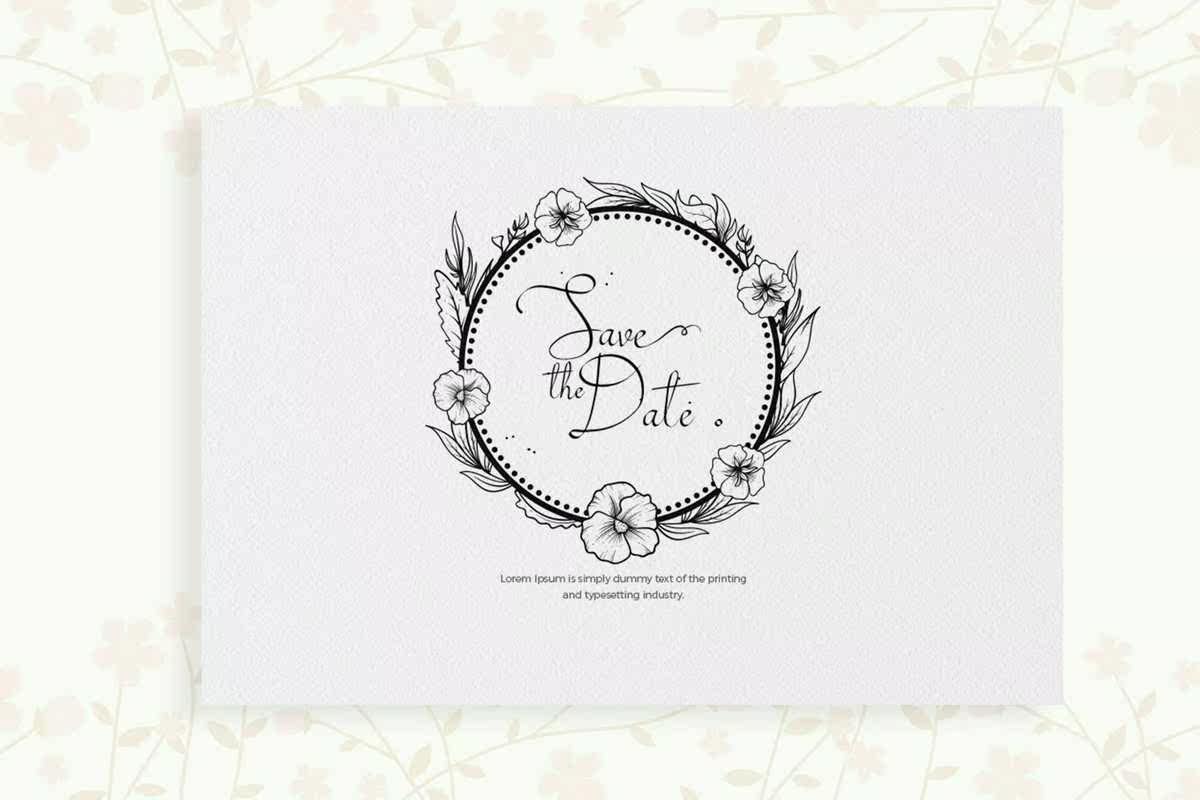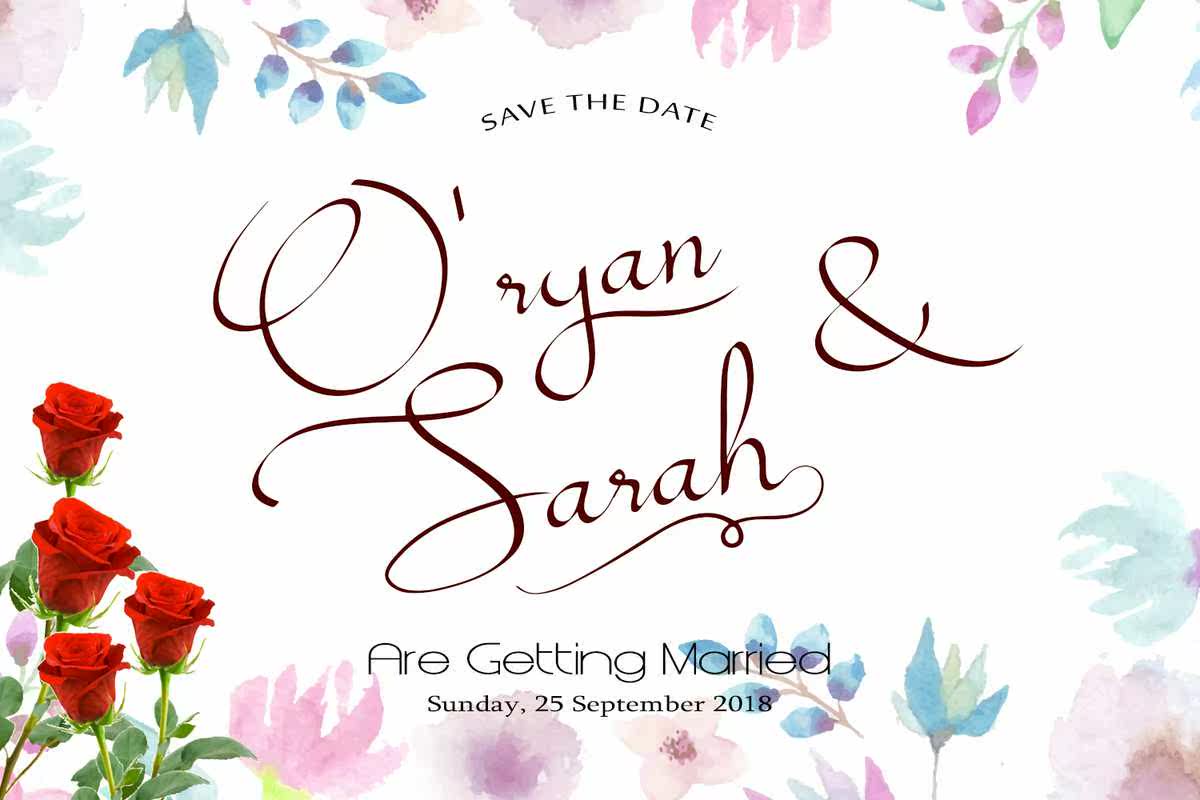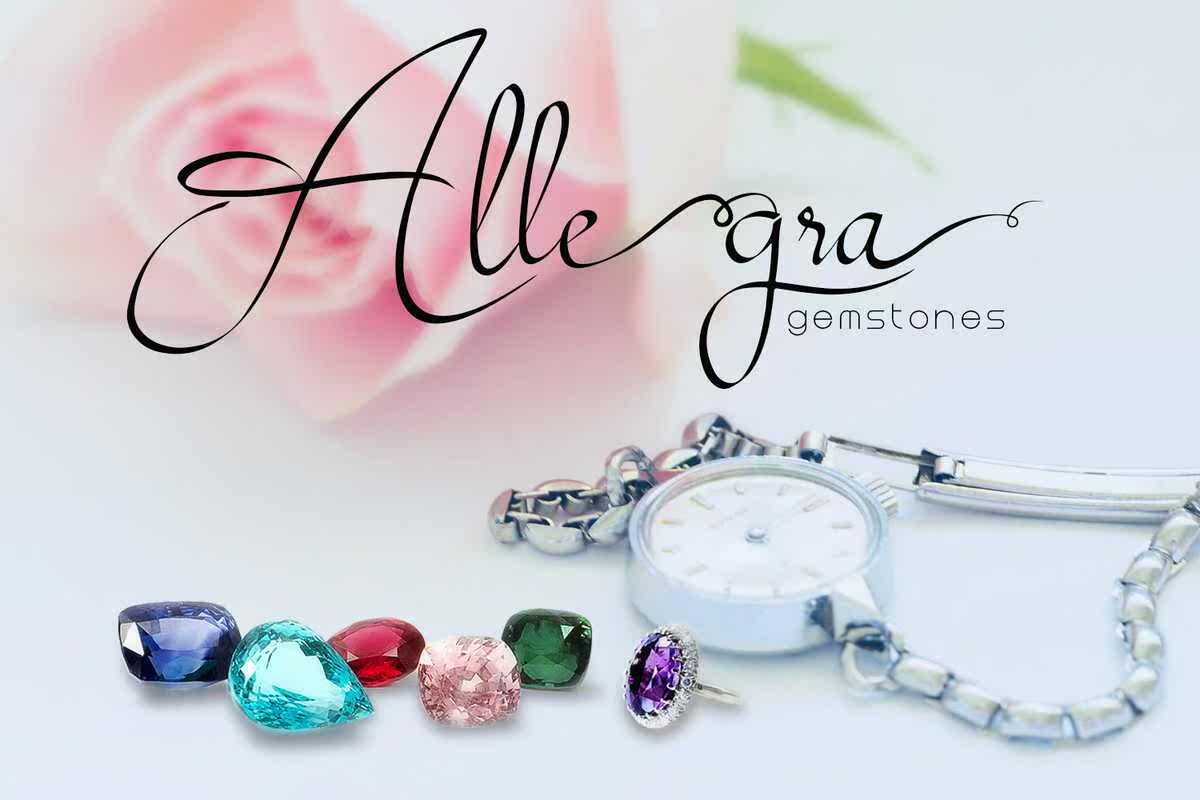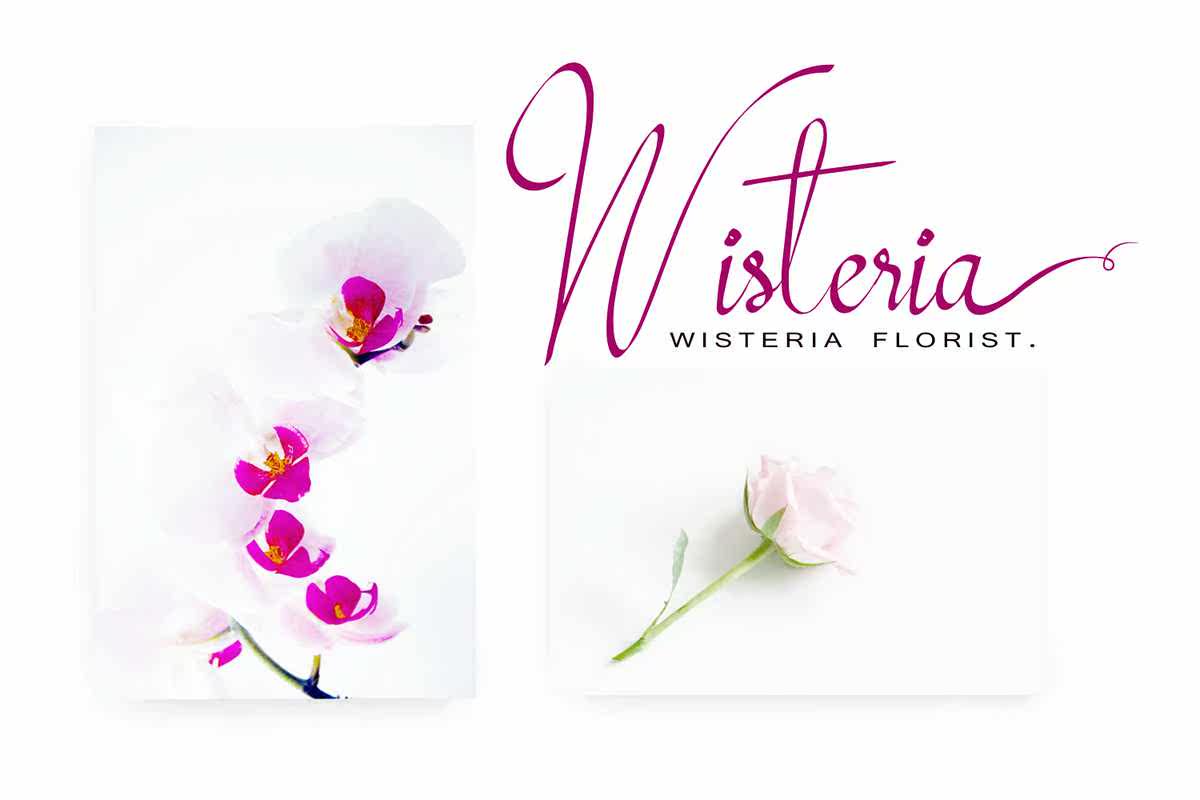
MollucasaAlligraphyTypeface(手绘)适用于品牌、婚礼邀请和贺卡、时尚和创意报价。Mollucash包括全套漂亮的大写和小写字母、数字、大量的假字符和连字以及风格替换,给出写实的手写体风格。您将获得:MollucasAsacalligraphyTypeface(手绘)它适用于品牌、婚礼邀请和贺卡、时尚和创意报价。Mollucash包括全套漂亮的大写和小写字母、数字、大量的假字符和连字以及风格替换,给出写实的手写体风格。您将获得: